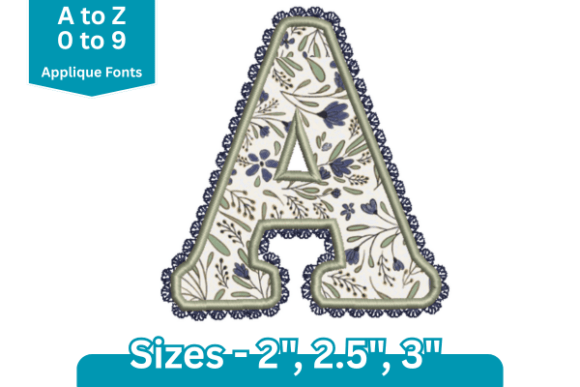
Lace Edge Applique Font
Jika Anda mencari aset berkualitas tinggi seperti Lace Edge Applique Font, paket premium ini adalah pilihan fantastis untuk proyek kreatif Anda.
Dibuat dengan presisi, Lace Edge Applique Font menyediakan vektor yang bersih, tipografi yang halus, serta lisensi komersial untuk ketenangan pikiran Anda.
Baik Anda membuat produk POD (Print on Demand), undangan pernikahan, atau grafis media sosial, Lace Edge Applique Font adalah pilihan yang sangat ideal.